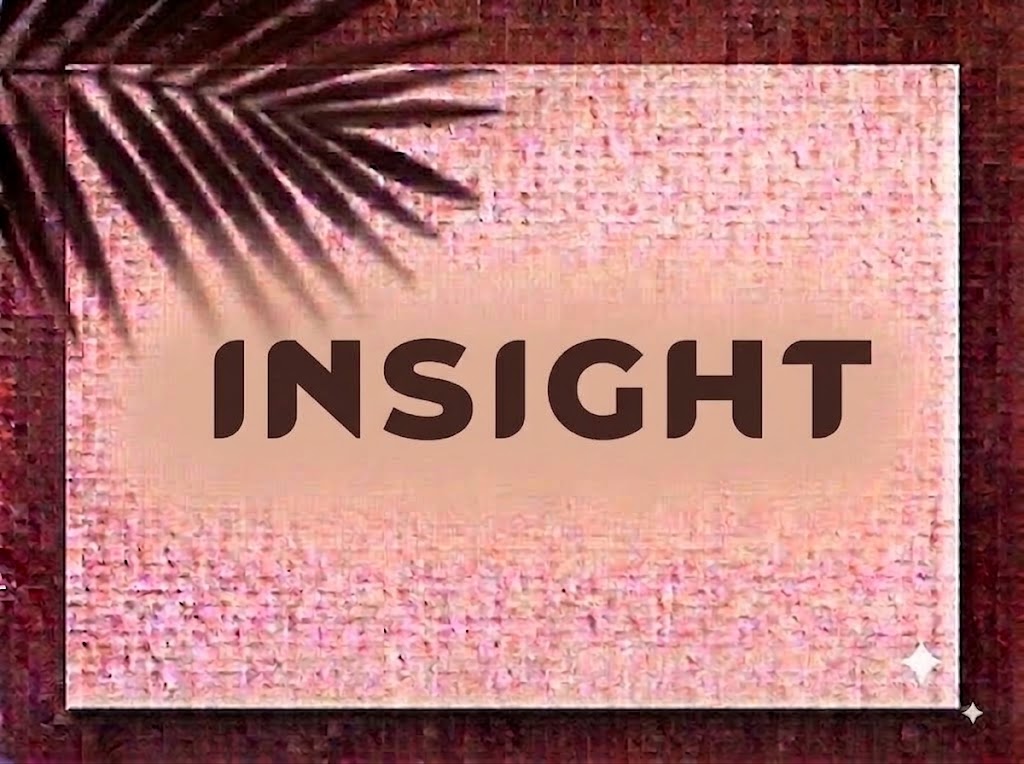
1FTV Krait Solid
Trong xu hướng thiết kế đồ họa đương đại, phong cách tương lai (Futuristic), công nghệ cao (Techno) và viễn cảnh viễn tưởng Cyberpunk luôn tạo nên sức hút bùng nổ. Những kiểu chữ sở hữu hình khối kiên cố, đường cắt vát hình học sắc lạnh cùng trọng lượng nét siêu dày (Solid) luôn là chìa khóa để biến dòng tiêu đề trở thành tâm điểm thị giác đầy uy lực.
Nếu bạn đang tìm kiếm một phông chữ hiển thị đậm chất máy móc, vũ trụ và gaming để làm logo đội tuyển eSports, poster giải đấu hay tiêu đề video ngắn bứt phá, font 1FTV Krait Solid chính là lựa chọn hàng đầu.
Giới thiệu về font 1FTV Krait Solid
Font 1FTV Krait Solid là bộ chữ hiển thị trang trí (display font) phát triển theo trường phái Futuristic & Geometric Techno, nổi bật với cấu trúc hình khối đặc sệt và các góc vát mang tính cơ học:
Tên phông chữ: 1FTV Krait Solid
Đặc điểm nổi bật của ngôn ngữ thiết kế Krait Solid
Sức hút thị giác của font 1FTV Krait Solid đến từ sự đan xen kịch tính giữa các mảng khối đen đặc và những đường xẻ vát góc cạnh:
Khối nét Solid siêu lực lưỡng: Đúng như tên gọi, phông chữ sở hữu khối nét cực dày, lấp đầy không gian hiển thị và mang lại cảm giác kiên cố như một khối kim loại đúc.
Đường cắt vát chéo & bo góc hình học: Điểm nhấn độc bản nằm ở những đường cắt góc nghiêng dứt khoát kết hợp cùng góc bo cong nhẹ ở các ký tự như
T,Q,K,R,O,X,J,S,D,B. Cấu trúc này gợi liên tưởng trực tiếp đến lớp giáp mecha, thân vỏ phi thuyền không gian hoặc giao diện máy viễn tưởng. -
Định dạng All-Caps kiên định: Toàn bộ hệ thống chữ cái được tạo hình in hoa, tạo nên sự liền mạch tuyệt đối khi dàn trang tiêu đề, giúp thông điệp luôn giữ vững tinh thần dứt khoát và thu hút ánh nhìn ngay từ giây đầu tiên.
Tối ưu hiển thị và dấu tiếng Việt từ 1FTV
Để phông chữ vận hành mượt mà trên cả Windows lẫn macOS, phiên bản này đã được tinh chỉnh kỹ lưỡng về mặt thông số nội tại:
Khoảng cách ký tự (Kerning): Khoảng cách giữa các chữ và tracking được cân chỉnh chuẩn xác, đảm bảo các khối chữ dày khi đứng sát nhau không bị bết dính hay che khuất đường cắt vát.
Bản Việt hóa chuẩn chỉnh: Hệ thống dấu thanh tiếng Việt (sắc, huyền, hỏi, ngã, nặng) cùng dấu mũ được thiết kế đồng điệu theo phong cách góc cạnh của bộ chữ gốc, đảm bảo không bị lỗi font hay đè dấu khi gõ cụm từ dài.
Hệ thống ký tự đồng bộ: Tích hợp đầy đủ dãy chữ số 0-9 phom dáng hầm hố cùng các ký tự dấu câu, ký hiệu thông dụng.
Đánh giá hiển thị thực tế
Khả năng hiển thị của phông chữ được tối ưu linh hoạt theo nhiều kích cỡ:
Kích thước nhỏ (12pt – 24pt): Nhờ độ tương phản mảng khối tốt, các câu ngắn và dãy số vẫn dễ dàng nhận diện trên màn hình điện thoại di động.
Kích thước lớn (36pt – 72pt): Đây là đất diễn lý tưởng nhất để 1FTV Krait Solid phô diễn toàn bộ vẻ đẹp gai góc, hiện đại và tính chất viễn tưởng cơ học, tạo tác động thị giác cực mạnh cho các dòng tiêu đề chính.
Ứng dụng trong thiết kế đồ họa và sản xuất video
Sở hữu nét cá tính đậm chất viễn tưởng, font 1FTV Krait Solid mở ra không gian ứng dụng phong phú:
Video ngắn (TikTok, Reels, Shorts): Dáng chữ đậm sắc lạnh cực kỳ ăn nhập với các clip gaming highlight, montage Valorant, CS:GO, Liên Quân, video âm nhạc EDM, Phonk, Trap hay review mô hình mecha, gunpla.
Ảnh thu nhỏ YouTube (Thumbnail): Lựa chọn hoàn hảo để giật tít cho các streamer, giải đấu game, video công nghệ AI hay phim khoa học viễn tưởng nhờ độ tương phản cao.
Nhận diện thương hiệu eSports & Gaming: Rất thích hợp làm logo dạng chữ khối cho gaming team, clan thể thao điện tử, streamer hay thương hiệu phụ kiện máy tính.
Poster Sự kiện & Thời trang Streetwear: Hoàn hảo cho poster lễ hội âm nhạc điện tử, bìa album DJ và in ấn phong cách Cyberpunk lên áo thun, áo khoác hoodie, áo thi đấu jersey.